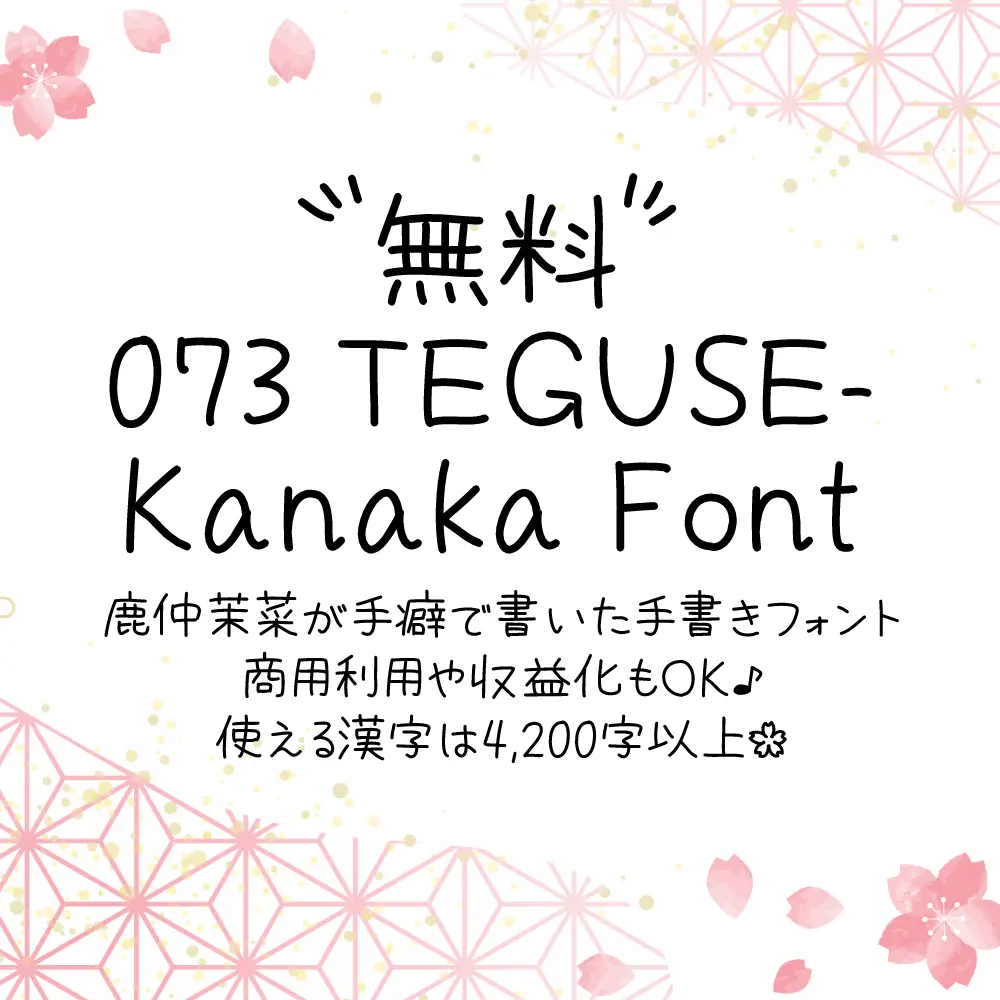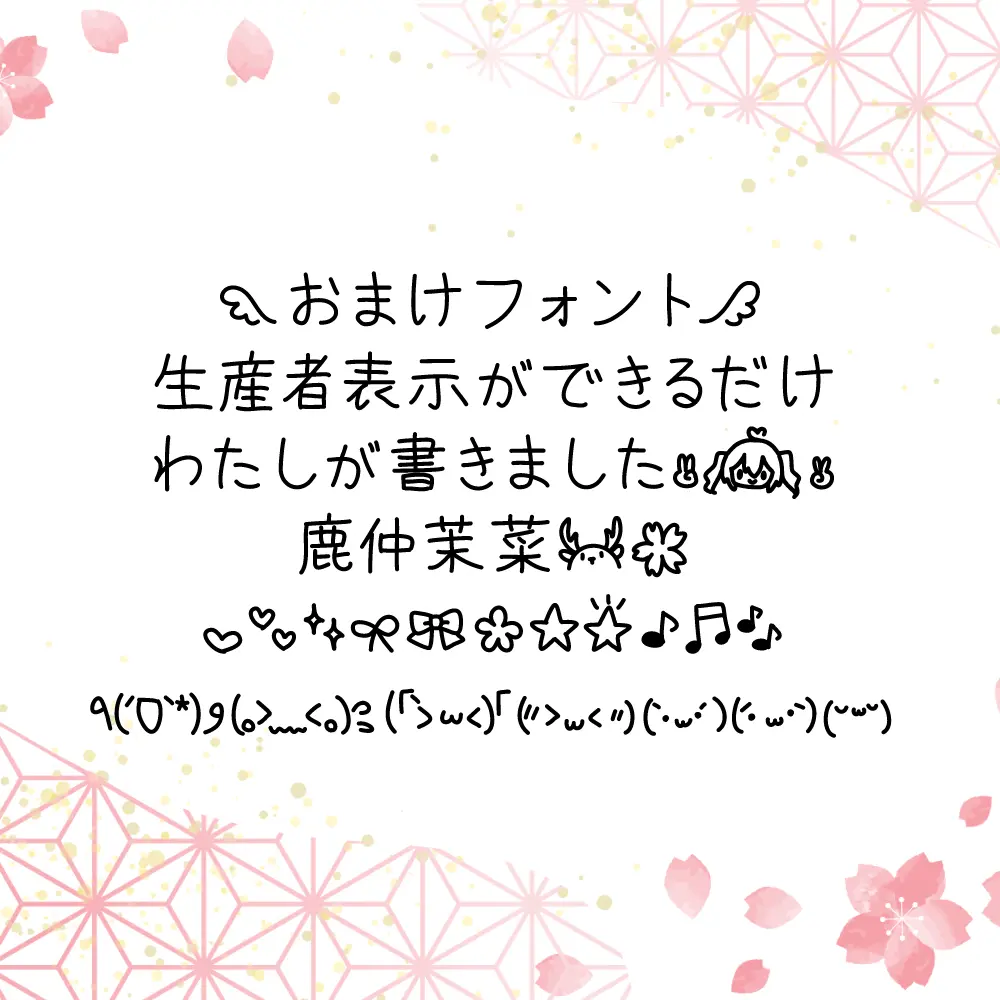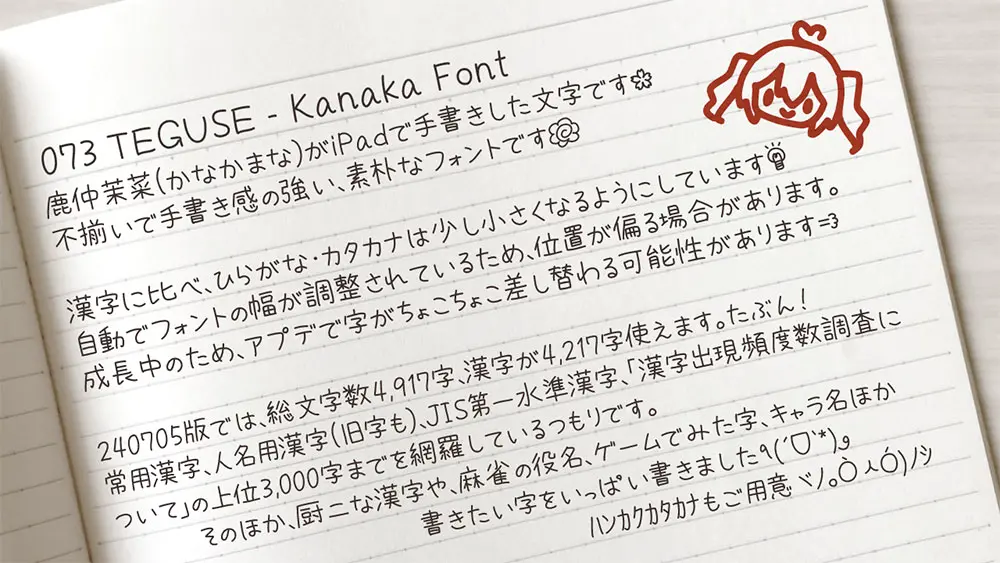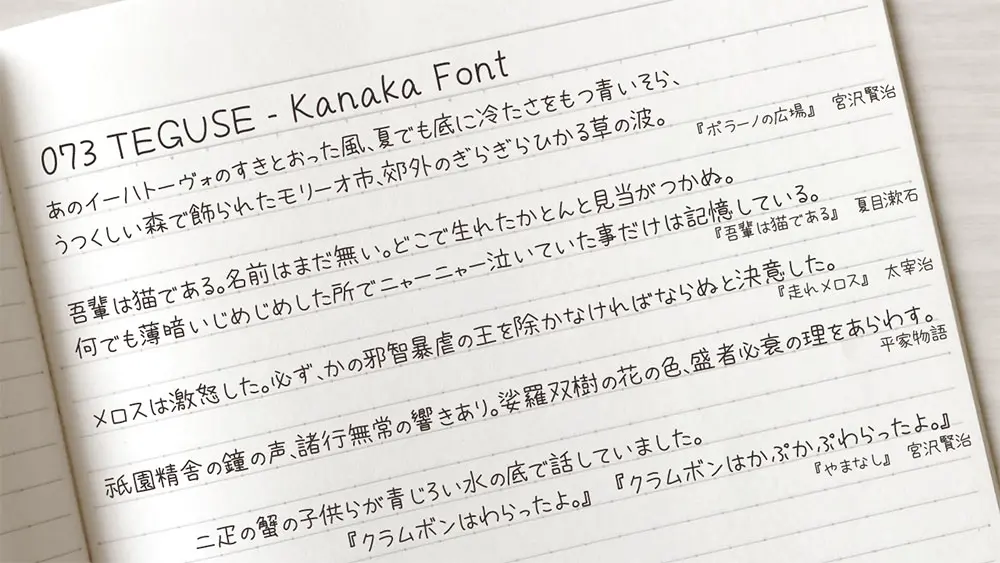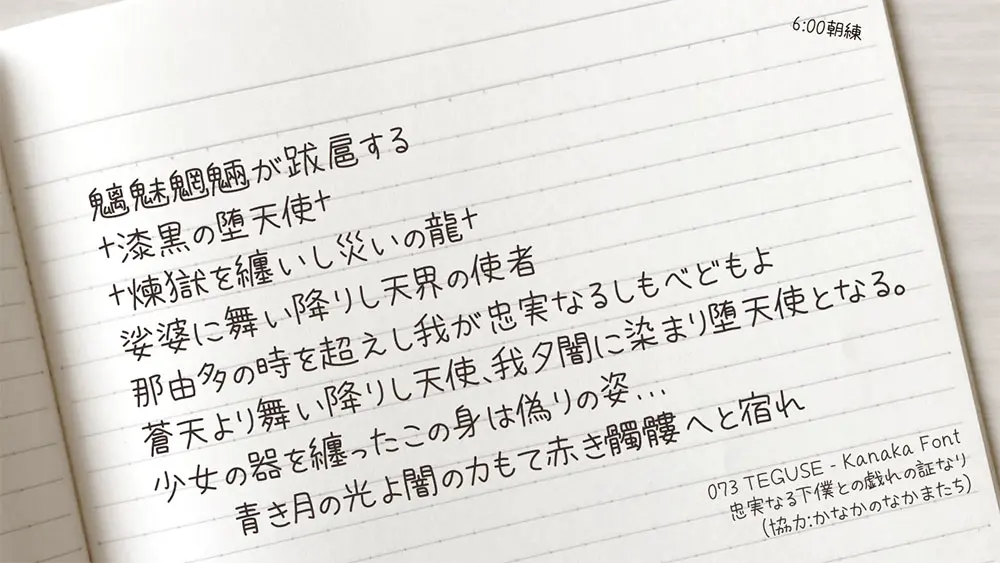
鹿仲茉菜の手書預覽
鹿仲茉菜の手書介紹
這是鹿仲茉菜的手寫字體。
是不整齊,手寫感強,樸素的字體。
與漢字相比,平假名、片假名要小一些。
自動調整字體寬度可能會導致位置偏移。
這個字體正在成長中。因為自己試著使用覺得平衡不好,或者覺得不擅長的字隨時都在修改,所以在應用程序中字有可能會稍微改變。
鹿仲茉菜(かなかまな)の手書きフォントです。
不揃いで手書き感の強い、素樸なフォントです。
漢字に比べ、ひらがな・カタカナは少し小さくなるようにしています。
自動でフォントの幅が調整されているため、位置が偏る場合があります。
このフォントは成長中です。自分で使ってみてバランスが悪いなと感じたり下手っぴすぎるなと思う字は隨時修正しているので、アプデで字がちょこちょこ差し変わる可能性があります。